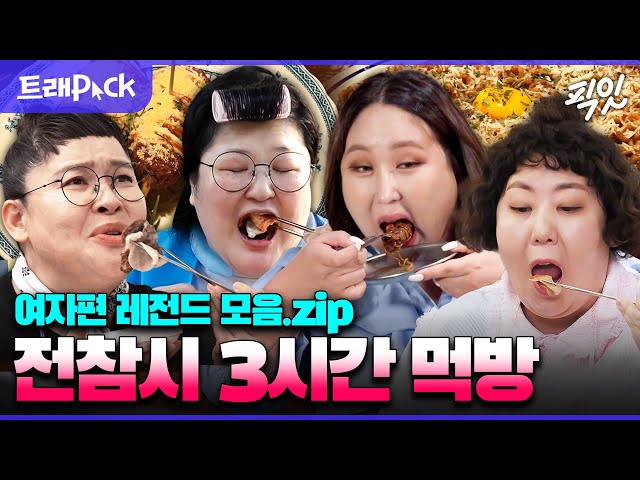
검은고딕 무료폰트
검은고딕 — ZESSTYPE에서 배포하는 무료 폰트입니다. 네모틀을 가득 채운 굵은 획으로 묵직한 시각적 무게감을 만드는 제목용 고딕체
제스타입이라는 서울 기반 독립 디자이너가 2015년에 만든 서체로, 2018년에 구글폰트에 올라 널리 쓰이게 됐습니다. 이름 그대로 가장 굵은 단계의 고딕입니다.
제작자가 만든 ZBLACK Original에서 파생됐고, 그 과정에서 글자 사이 간격을 조정하고 높이와 폭을 구조적으로 통일해 가독성을 개선했다고 밝히고 있습니다. 네모꼴을 강조해 헤드라인과 타이틀에 쓰도록 설계했다는 설명도 붙습니다.
한글은 2,581자로 완성형 전체는 아닙니다. 직접 확인해 보니 일상적인 낱말은 문제없이 나오고 아주 드문 음절에서만 빠집니다. 굵기는 하나뿐이고 제목 전용이라 본문에는 맞지 않습니다. 오픈 폰트 라이선스로 배포되어 수정과 재배포가 자유롭고 BI와 CI에도 쓸 수 있습니다.